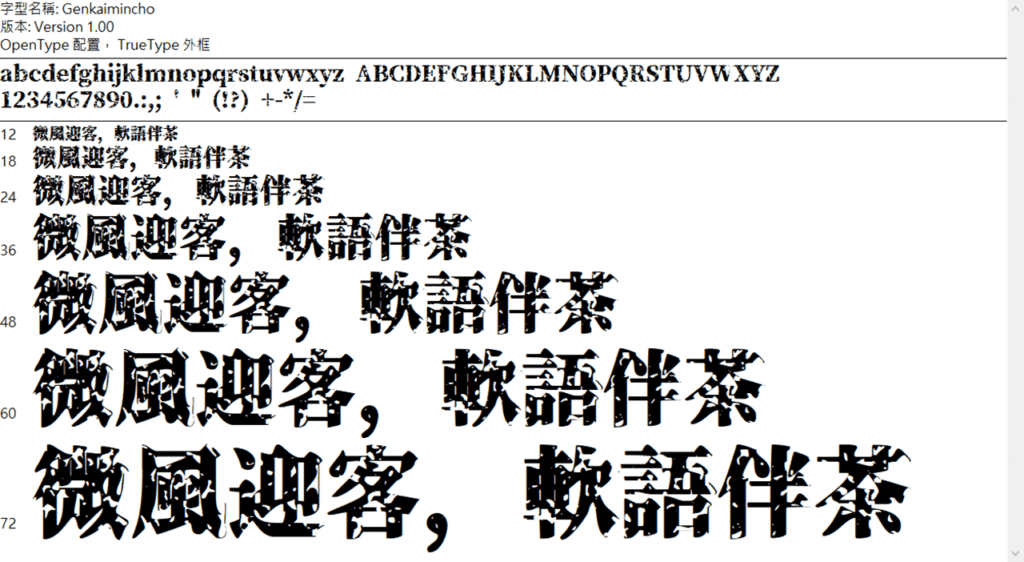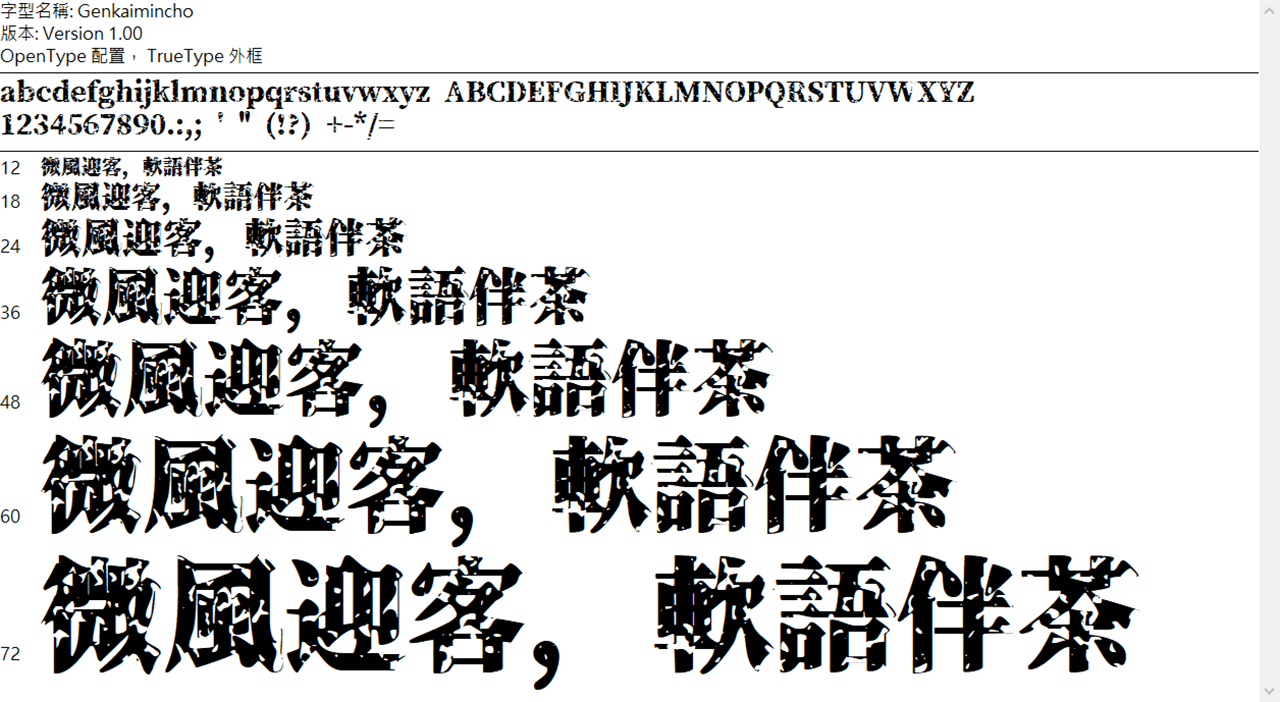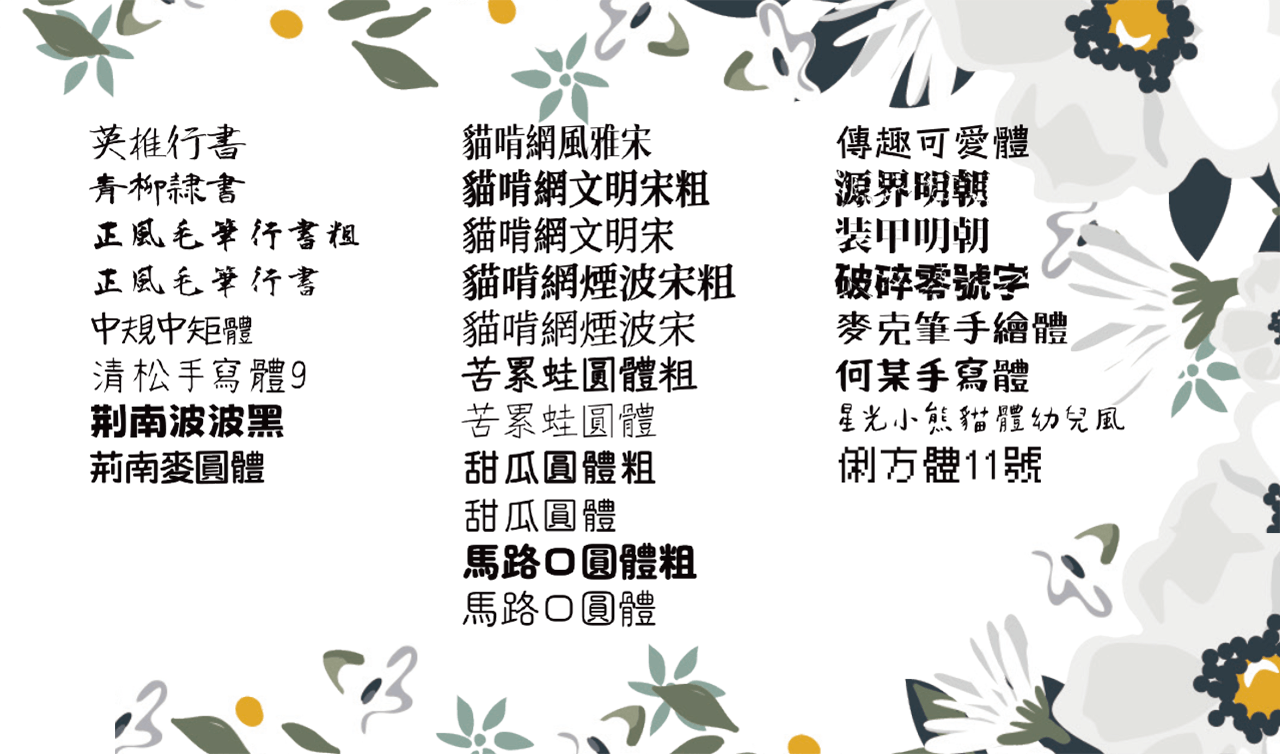
DIY 線上設計平台「設計雲」2026 年新增的開源免費中文字體
又來到「設計雲」 線上平台新增字體時刻,2026 年版已累積了二十多款的免費開源中文字體,如下圖的字體表列。此次新增了《貓啃網提供的自家字體》,日本 FLOP DESIGN 設計的優質日文字體,以及日本書法家青柳衡山的毛筆書法字型等,都是採相同的 SIL Open Font License 授權方式。
2026 年新增的中文字體
包含貓啃網自家的文明宋、煙波宋和風雅宋三款宋體,補齊了「人文感」與「復古美學」的缺口。這三款字體均由「新愚公」改造開發,並由「貓啃網」優化發布。
貓啃網文明宋
日本 FLOP DESIGN 設計的字體有源界明朝、裝甲明朝和破碎零號字。源界明朝是以「思源宋體」為基礎,加入破壞效果,可以想像是思源宋體的破壞版。裝甲明朝也是以「思源宋體」為基礎加以改造,橫筆畫特別細。破碎零號字是將「思源黑體」字體修改而產生的衍生字體。
源界明朝
繼加入《免費毛筆書法字型》的莫大毛筆之後,因為客戶還蠻喜愛這類字體,再新增有正風毛筆行書、青柳隷書與英椎行書。皆出手自日本書法家青柳衡山的「衡山毛筆行書フォント」,並已彌補繁體中文常用字缺字,這都要感謝網友 Max 的努力付出與分享。
青柳衡山之書法字型
網友 Max 的貢獻除了前述的「毛筆書法字型」,還有改造出許多的免費字體,這次包含了馬路口圓體、苦累蛙圓體和何某手寫體。族繁不及備載,有興趣自行至網站瀏覽下載。
其餘的字體如「俐方體11號」是開源繁體中文點陣字型,「甜瓜圓體」(Mamelon Hi) 因為字體相當可愛且免費,深受台灣的字體使用者歡迎,以及荆南字坊的波波黑體和麥圓體。其他的字體就不再贅述了,自己試用看看。